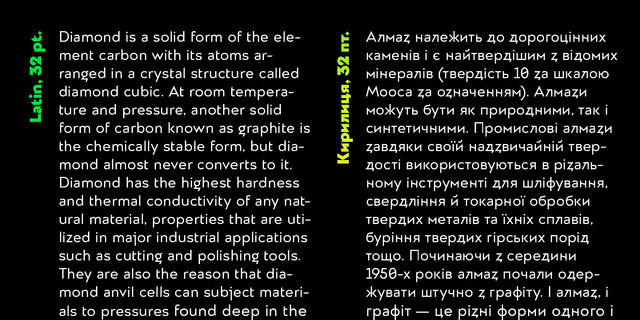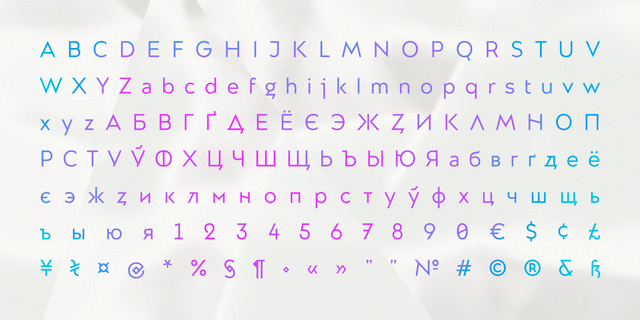
Almaz – это современный геометрический гротеск, вдохновленный украинским модернизмом 20-го века. Он имеет динамические формы букв и авангардный характер. Шрифт спроектирован для логотипов, заголовков, книжных обложек, айдентики, также может использоваться для набора небольших объемов текста. Гарнитура состоит из 9 насыщенности (от супертонкого к ультражирного). Шрифт разработали Сергей Макаренко и Кирилл Ткачев в 2020 году.
острый, треугольный, звонкий, чистый, твердый, качественный, модный, точный, холодный, невесомый, легкий, прозрачный, худой, стеклянный, хрупкий, ювелирный, кристальный, колючий, резкий, четкий, стальной, странный, архитектурный, городской, оригинальный, самобытный, характерный, дорогой, роскошный, богатый, динамичный, зимний, ледяной, творческий, необычный, музыкальный, смелый, амбициозный, экстравагантный, мотивирующий, активный, игривый, дерзкий, ночной, опасный, броский, заметный, яркий, тяжелый, щедрый, артистичный, выразительный, устойчивый, урбанистический, сильный, мощный, громкий, навязчивый, осколочный, тусовочный, клубный, движняковый, экстремальный, рискованный, эпатажный, агрессивный, экспрессивный, жесткий, радикальный, черный, тесный